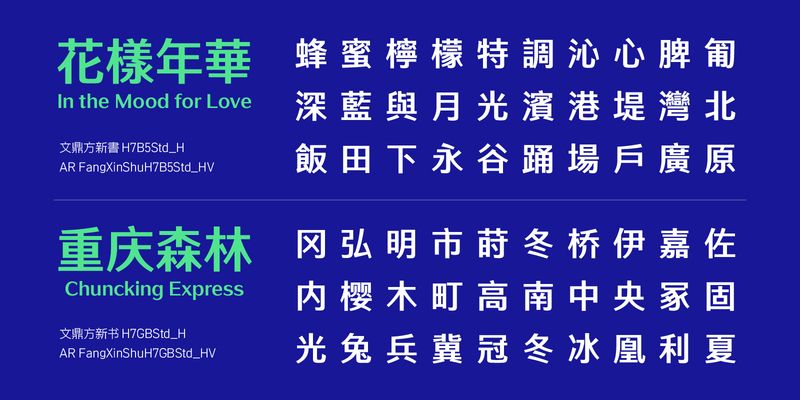
La police FangXinShu s’inspire du style de la période Heian dont elle tire la concision et la régularité, tout en intégrant le confort et l’élégance de la période Ming ; Arphic utilise des spécifications rigoureuses pour examiner l’identifiabilité des titres et la lisibilité du texte, afin d’offrir aux utilisateurs la meilleure expérience d’utilisation.